Alors que les feuilles changent de couleur et quâun froid sâinstalle dans lâair, la saison de la peur sâabat sur nous. Halloween, une fĂȘte bien-aimĂ©e cĂ©lĂ©brĂ©e dans le monde entier, offre une occasion passionnante de libĂ©rer votre cĂŽtĂ© crĂ©atif. Des dĂ©corations macabres aux invitations Ă©tranges, lâesthĂ©tique dâHalloween joue un rĂŽle central en donnant le ton aux festivitĂ©s. Un Ă©lĂ©ment clĂ© qui peut vous aider Ă capturer l'esprit de ces vacances obsĂ©dantes est l'utilisation depolices d'Halloween .
Dans cet article, nous plongerons dans le monde captivant des polices d'Halloween, en explorant comment insuffler Ă vos crĂ©ations d'Halloween une essence effrayante, les divers styles de polices d'Halloween disponibles et oĂč trouver ces polices gratuitement !
5 conseils pour donner à vos créations un style Halloween
La typographie est un outil de conception puissant qui peut transmettre instantanĂ©ment des ambiances et Ă©voquer des Ă©motions. Lorsquâil sâagit de designs sur le thĂšme dâHalloween, la bonne police peut transporter votre public dans un monde de mystĂšre et dâintrigues. Voici quelques conseils pour donner Ă vos crĂ©ations un style Halloween incomparable en utilisant des polices.
1. Choisissez la bonne police de caractĂšres
Optez pour des polices qui dĂ©gagent une ambiance Ă©trange. Les polices gothiques avec des arĂȘtes vives, des empattements et des Ă©lĂ©ments dĂ©coratifs peuvent instantanĂ©ment crĂ©er une ambiance effrayante. Des polices comme « Chiller », « Nosferotica » et « Gotham Nights » sont dâexcellents choix pour les designs inspirĂ©s dâHalloween.
2. Jouez avec les ligatures et les mots
Une ligature se produit lorsque deux lettres ou plus sont jointes pour former un seul mot .
Certaines polices Spooky Halloween proposent des ligatures et des mots uniques qui ajoutent une touche de fantaisie Ă vos crĂ©ations. Recherchez des polices contenant des chauves-souris, des araignĂ©es, des citrouilles ou d'autres caractĂšres sur le thĂšme d'Halloween pouvant ĂȘtre utilisĂ©s comme caractĂšres spĂ©ciaux dans votre texte.
3. Ajustez l'espacement des lettres et le crénage
Le crénage est l'espacement entre des lettres ou des caractÚres individuels .
ExpĂ©rimentez avec l'espacement des lettres et le crĂ©nage pour amĂ©liorer l'attrait visuel de votre texte. Des formes de lettres lĂ©gĂšrement allongĂ©es ou condensĂ©es peuvent contribuer Ă lâatmosphĂšre globale hantĂ©e.
4. Incorporer la texture
De nombreuses polices effrayantes sont accompagnĂ©es de variations texturĂ©es ou vieillies qui peuvent donner une apparence vintage et Ă©trange Ă vos crĂ©ations. Ces textures peuvent simuler un parchemin vieilli ou lâaspect patinĂ© dâun tome oubliĂ©.
5. Mélangez judicieusement les polices
Pour ajouter de la profondeur et du contraste, pensez à combiner différentes polices dans un design. Associer une police de titre audacieuse et accrocheuse avec une police de corps plus sobre peut créer une hiérarchie visuelle dynamique.
Styles de police d'Halloween disponibles
Le monde des polices est un trésor de styles divers qui répondent à différents goûts et préférences de conception. Que vous recherchiez une ambiance de film d'horreur classique, un look ludique et adapté aux enfants ou une élégance gothique, il existe un style de police qui correspond à votre vision.
Effrayant et déformé
Ces polices incarnent les aspects troublants et effrayants dâHalloween. Les personnages peuvent paraĂźtre tordus, dĂ©formĂ©s ou dĂ©goulinants dâune aura dâun autre monde. Des polices comme « Creepster », « Distorted Faith » et « Toxic Type » entrent dans cette catĂ©gorie.
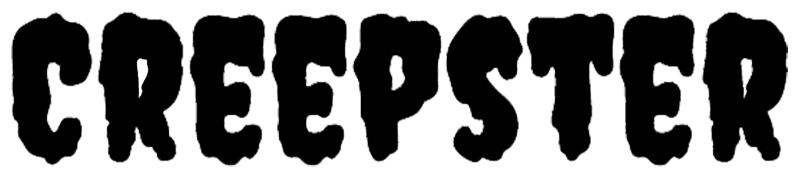
Mignon et ludique
Idéales pour les créations d'Halloween adaptées aux familles, les polices mignonnes et ludiques présentent des monstres sympathiques, des citrouilles souriantes et des personnages fantaisistes. Ces polices établissent un équilibre entre les racines effrayantes des vacances et une approche légÚre. Les exemples incluent « Halloween Spider », « Trick or Treat » et « Boo Yah ».
Gothique et élégant
Si vous recherchez une atmosphÚre plus sophistiquée et gothique, les polices de cette catégorie sont votre meilleur choix. Avec des détails complexes et des fioritures ornées, ces polices évoquent un sentiment de romance sombre. Des polices comme « Gothicus », « Vampiro One » et « Victorian Parlour » illustrent ce style.